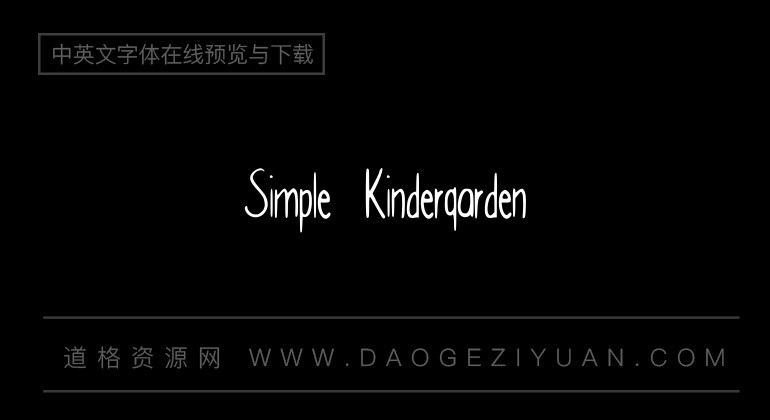
Simple Kindergarten 是一款为幼儿园和儿童设计的字体。它采用了大胆简洁的线条和圆润的形状,字母间距较大,字符轮廓清晰易读。该字体还包括一些特殊字符,例如数字和标点符号,这些字符也使用了与字母相同的简单风格。 Simple Kindergarten 字体旨在帮助幼儿园和儿童更好地阅读和书写文字,尤其适合用于教学材料、绘本、游戏和其他儿童相关的设计项目中。它的设计简单、可爱,同时不失清晰易读,是一款非常适合儿童群体使用的字体。内容介绍
Simple Kindergarden是一款非常不错的手写艺术字体,具有很好的视觉感,适合于文化类的宣传设计、商业类品牌的广告和产品包装设计以及个性化文字排版等较多场景。